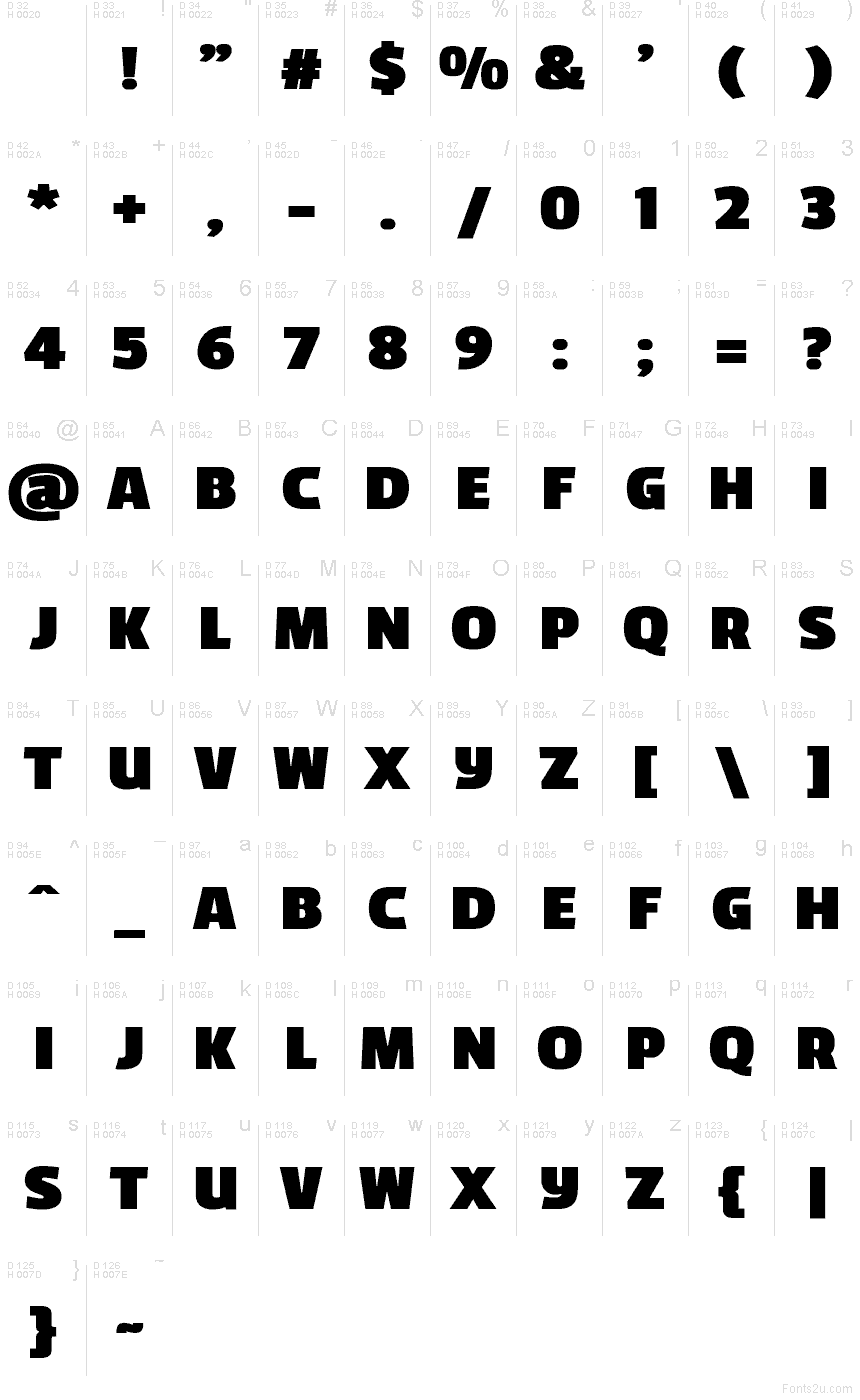
Energy, de Graphicxell, es una tipografía sans serif gratuita en caja alta con una actitud contundente, diseñada para carteles. Las letras tienen un corte ancho y pesado, mezclando bloques cuadrados con algunos cortes angulares afilados y giros redondeados, por lo que la fuente se siente rápida, compacta y ligeramente futurista sin perder su fuerza bruta.
Funciona bien para branding deportivo, flyers musicales, títulos de juegos, gráficos para eventos tecnológicos y titulares cortos en packaging donde una fuente gratuita necesita impactar con peso inmediato. Úsala para portadas, tarjetas de título o logotipos grandes: las formas densas y los detalles recortados dan incluso a las frases cortas un impulso cargado y comprimido.